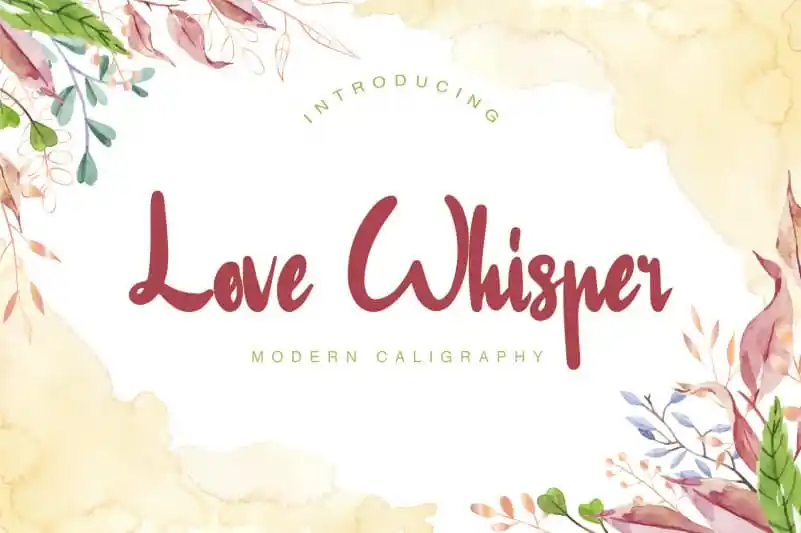
Love Whisper Script Font – Download Grátis
A Love Whisper Script Font é uma elegante tipografia feita à mão que transmite romantismo e suavidade. Ideal para diversos usos, desde logotipos até cartões de convite de casamento, estampas de camisetas, selos de correspondência e material publicitário. Seu traço delicado e fluido permite uma aplicação ampla, tornando-a um recurso inigualável para designers em busca de adicionar romantismo a seus projetos. Composta pelo designer Heloyud, esta fonte é perfeita tanto para aqueles que desejam um toque romântico em seu trabalho quanto para os amantes da arte da escrita tipográfica. Sinta-se à vontade para explorar todas as possibilidades criativas desta fonte única e encantadora.